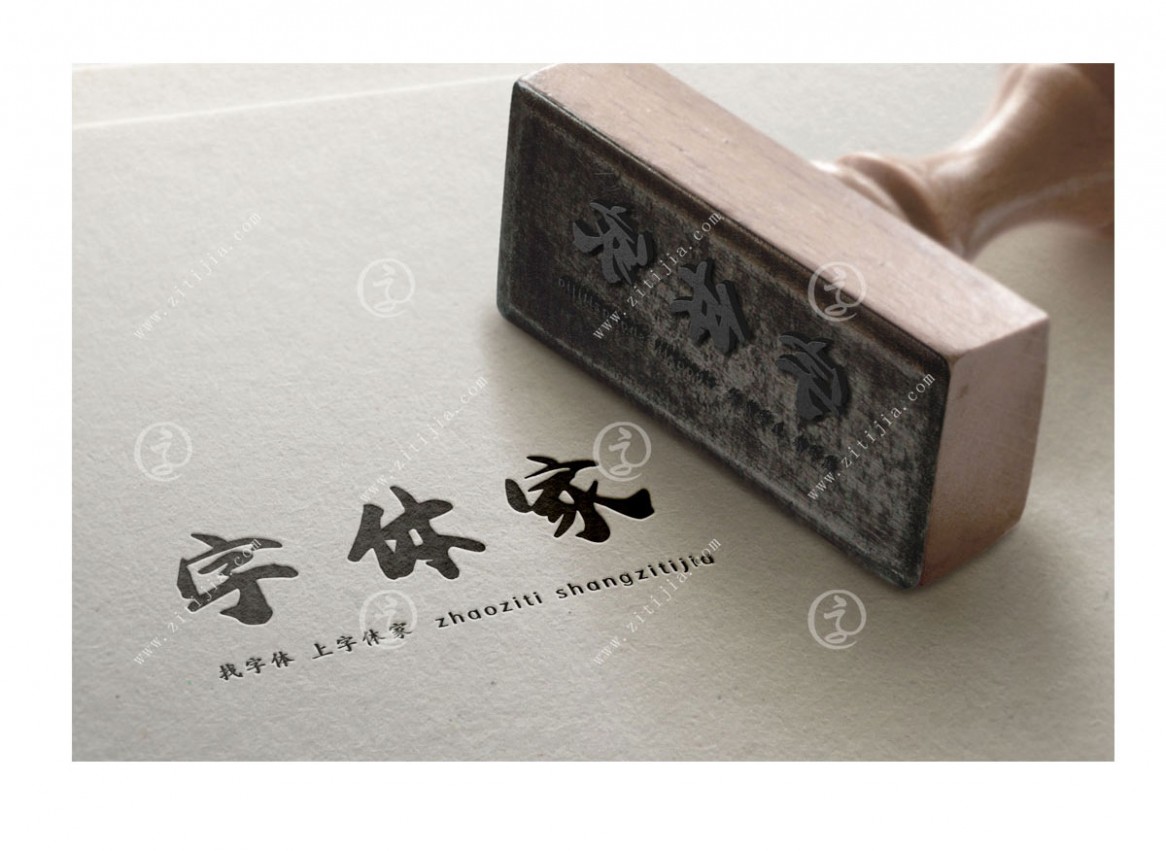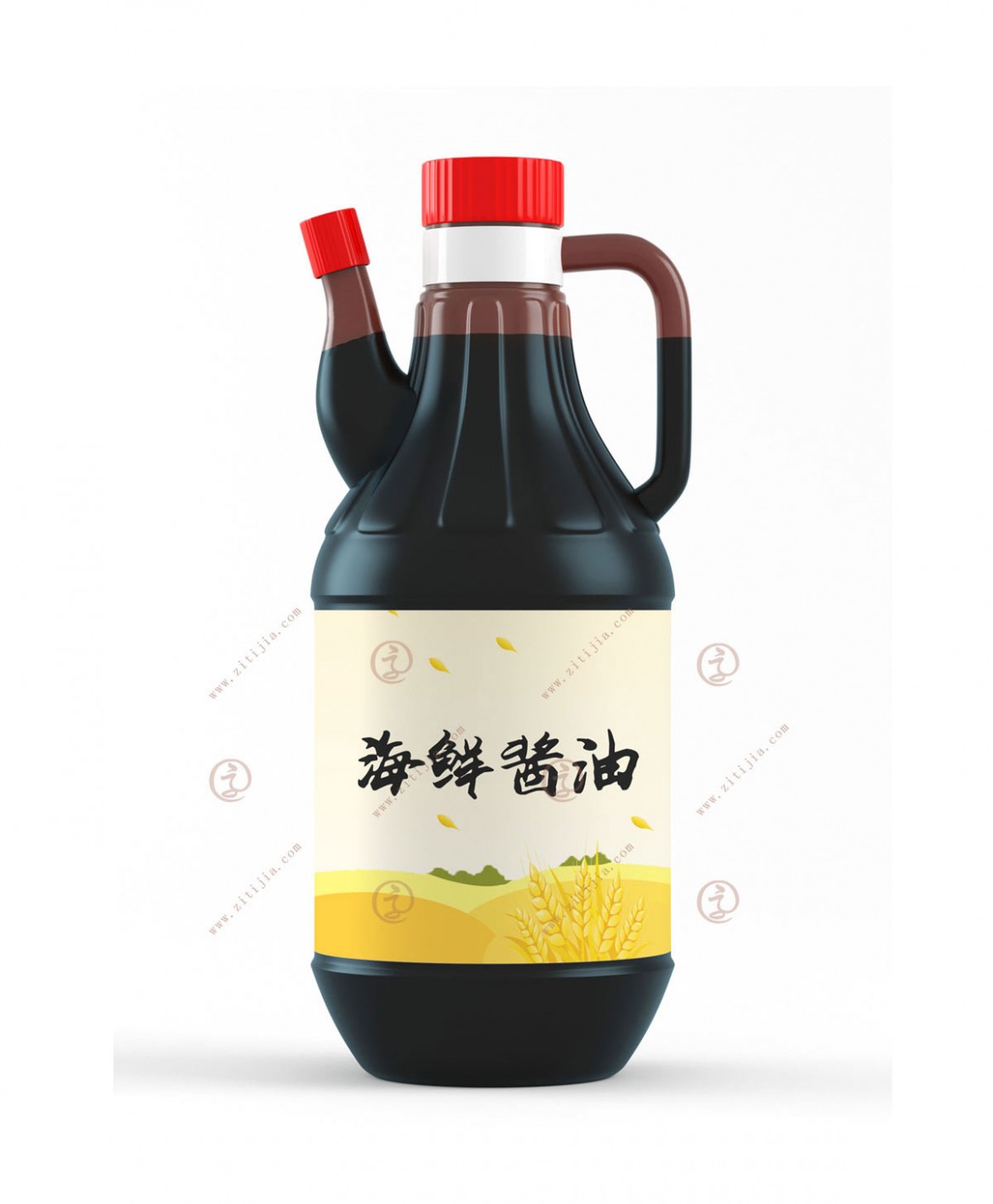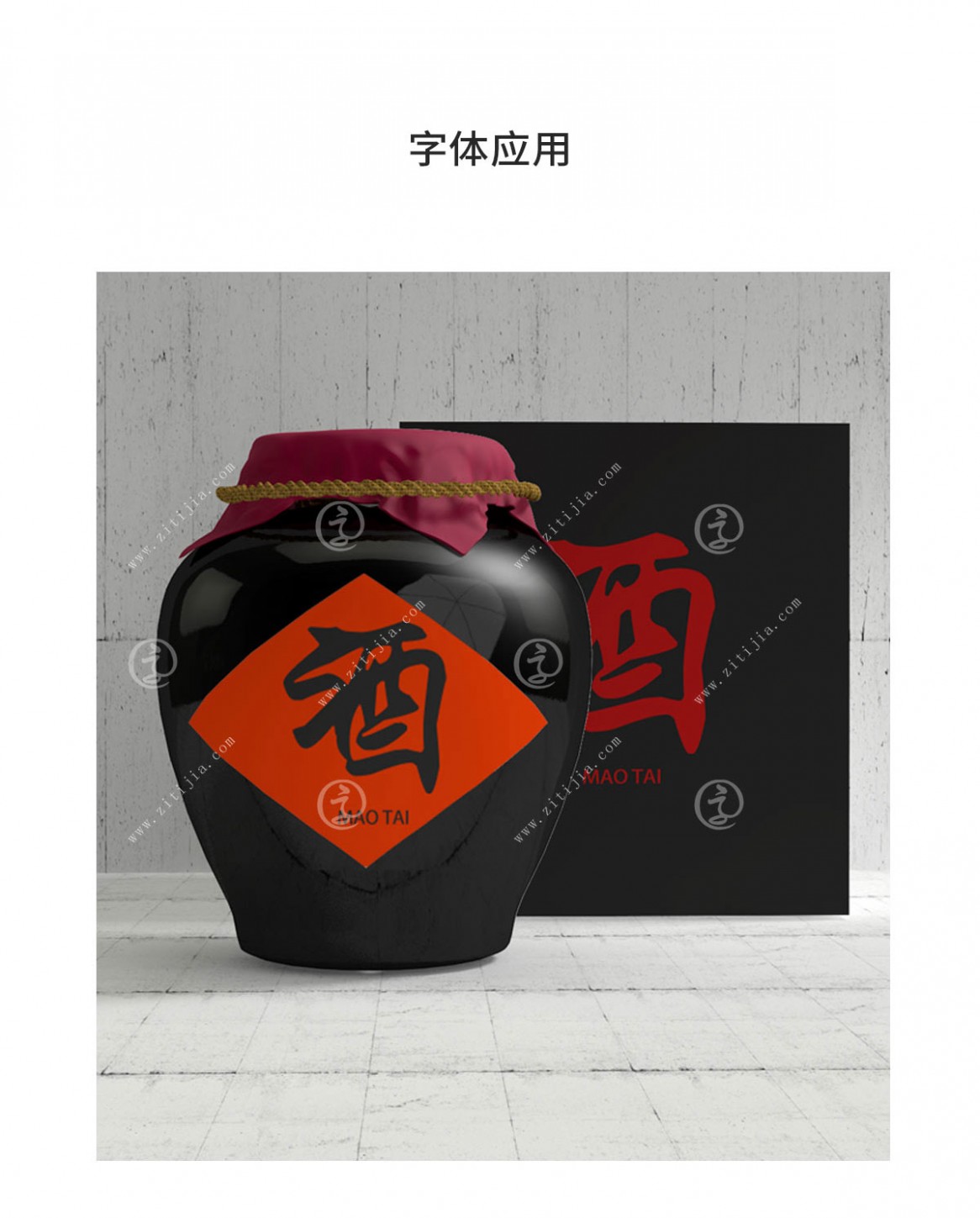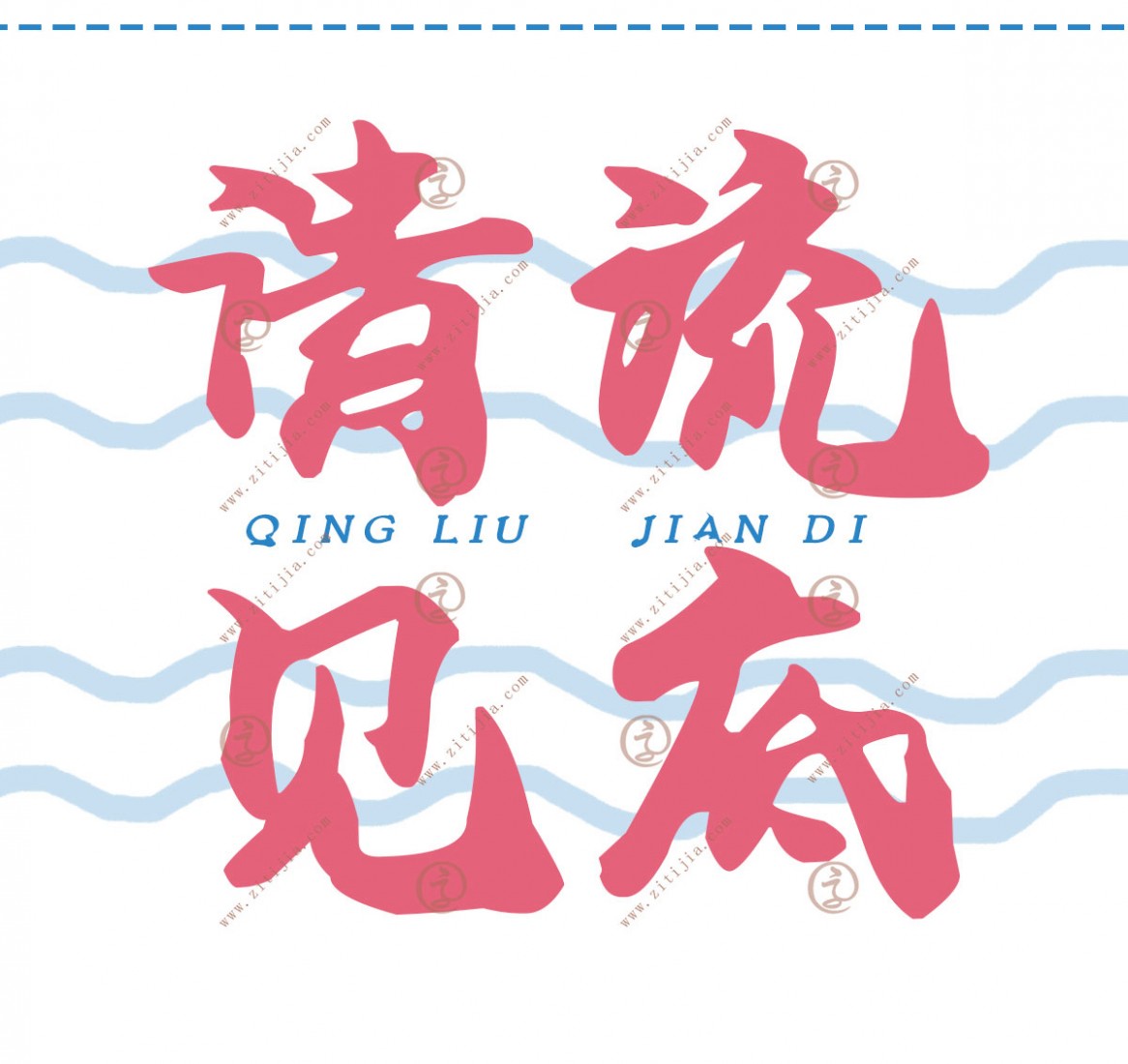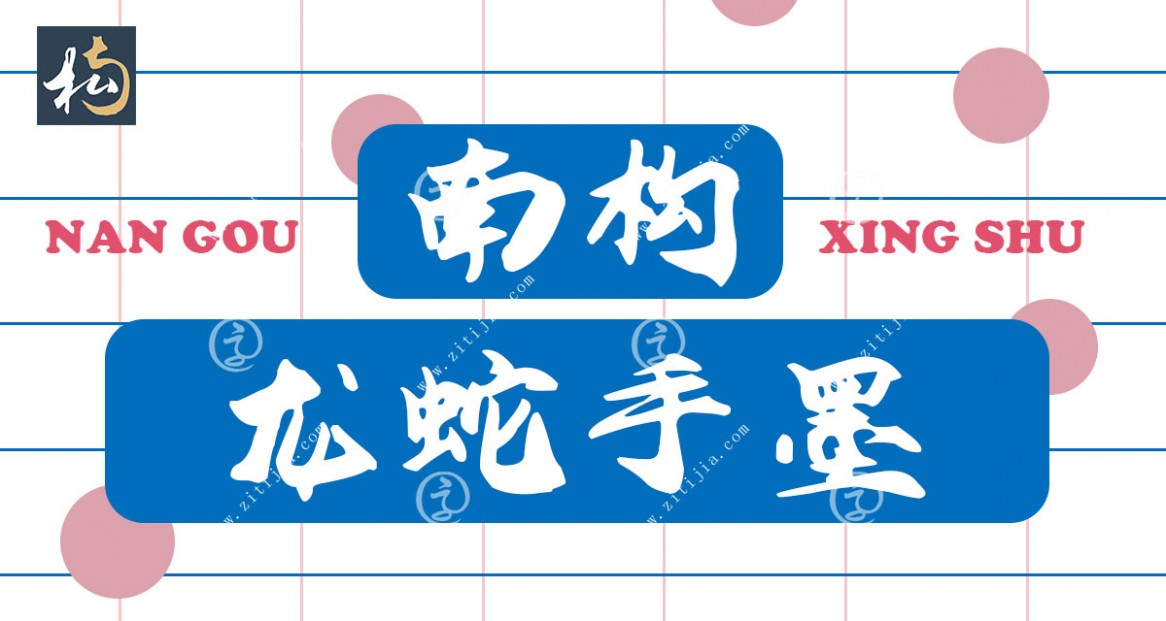
南構(gòu)龍蛇手墨
這是一款由字體家平臺南構(gòu)字庫獨(dú)家制作發(fā)行的字體,筆墨龍蛇中游走于漢字筆畫間,所有的情感都注定在這橫豎撇捺中侵融而就,是廣告招牌,海報(bào)設(shè)計(jì)以及相關(guān)標(biāo)題用字,中國風(fēng)書法題材不錯(cuò)的選擇。